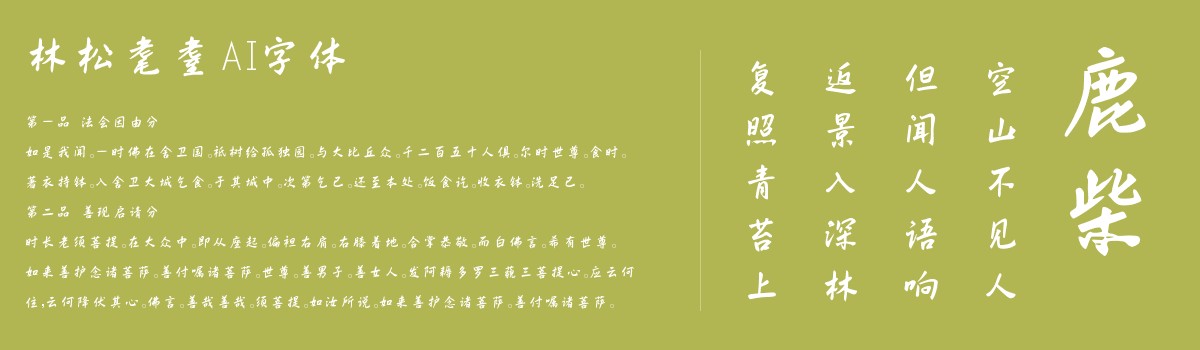
94岁高龄的老年人书写了9个字,用字体家AI神笔做成了一套AI字库。
年龄最高的人出品的AI字库。
94岁高龄老人在书写了9个书法字
利用这9个字,我们把它处理成白底黑字
把字处理成白底黑字再通过字体家AI神笔造字系统进行选择纸上造字
纸上造字分离技术
分离技术需要处理成白底黑字,且字的周围尽量没有黑点,干净,这样做出来的AI字体效果才会更好
AI字体模型效果1
AI字体模型出来了,效果还不错的,上面一行是分离出来的原字,下面一行是AI造字系统根据原字出来的AI字体成品,根据这个就可以生成一整套完整中文字库。
字体生成字体命名为林松耄耋AI字库
字体已经生成了,命名为“林松耄耋AI字体”,因为是94岁高龄,称为耄耋之年,把年龄属性加到字体名称中。
林松耄耋AI字体生成3
字体已经生成了,效果还是有保留了一定的书法手写体的味道。